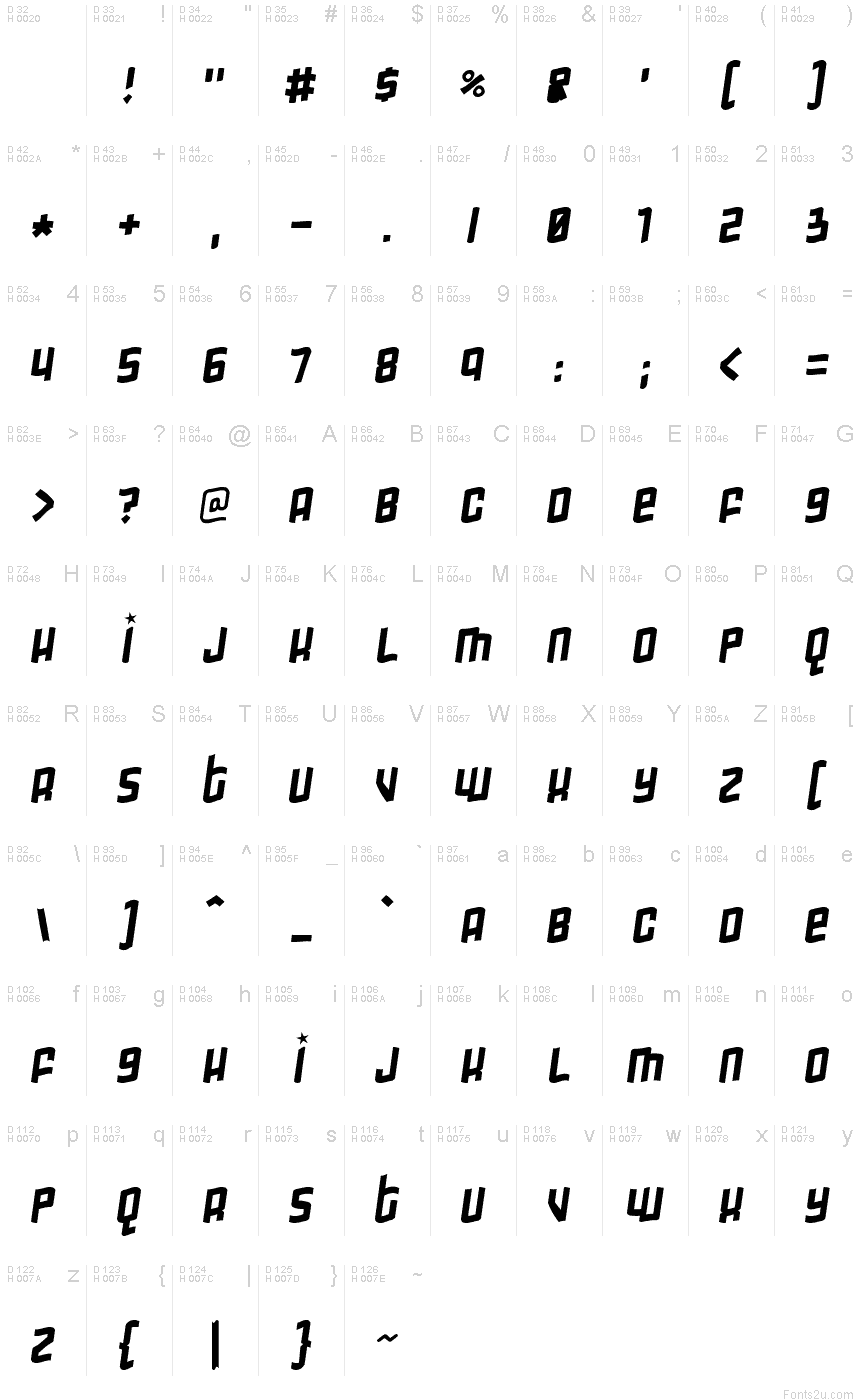
Gimmicky di Jakob Fischer è un font display gratuito in stile comic, che irrompe sulla pagina con un’energia vivace e fuori dagli schemi. Ogni lettera si inclina e oscilla leggermente, con tratti spessi e angoli morbidi che sembrano disegnati con un pennarello grosso su carta lucida da poster. Il ritmo è sciolto ma sicuro, ideale per dare ai titoli una presenza divertente e decisa senza mai scivolare nel caos.
Gimmicky